儿童节不只是孩子的节日,每个人都有专属于童年的记忆。难忘的童年片段,在泛黄的老照片上清晰起来。 怀旧不念旧,永远保持一颗年轻的心。在这个充满欢乐的节日里,字体视界携手三极字库为大家带来一波可爱又好看的字体,我们一起来欣赏。
三极露融体这款字的特征巧妙融合了时代审美,曲直结合、柔中带刚、撇捺对称 、由细到粗、曲线弧度谦逊而温婉;灵感来源于清晨的露珠,朝气蓬勃,整体蕴含生机和坚韧力量。该字体目前拥有3款不同的字重,适用于搭配标志、广告标语、商业广告、海报字体等。
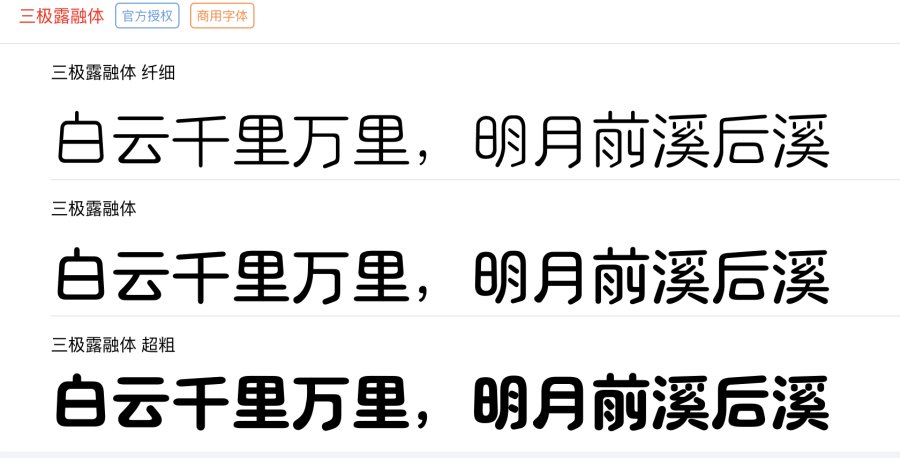
三极花朝体来源于花朝节,“百花生日是良辰,未到花朝一半春;万紫千红披锦绣,尚劳点缀贺花神。”清人蔡云的这首《咏花朝》就是民间庆贺百花生日风俗盛况的写照。这款字体笔画横平竖直,粗细适中,疏密布局合理,使人看起来清晰爽目,遒劲有力神韵超逸,瘦劲清峻。用于内文中规整又不失活跃感,让人印象深刻,适用于各种书写印刷文本需求,是款必选的字体。目前这款字体在字体视界平台已经上线了4种不同的字重,后续为您持续更新。